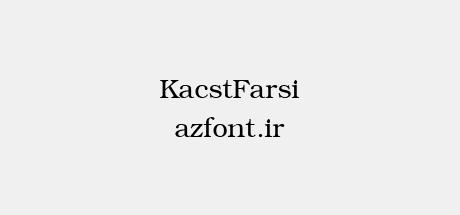
KacstFarsi
فونت زیبای رایگان KacstFarsi
قلم زیبای KacstFarsi از سری قلم های بسیار زیبا برای تایپوگرافی و لوگو تایپ می باشد.این قلم در وزن Regular و توسط Maurice Jabre طراحی و منتشر شده است.